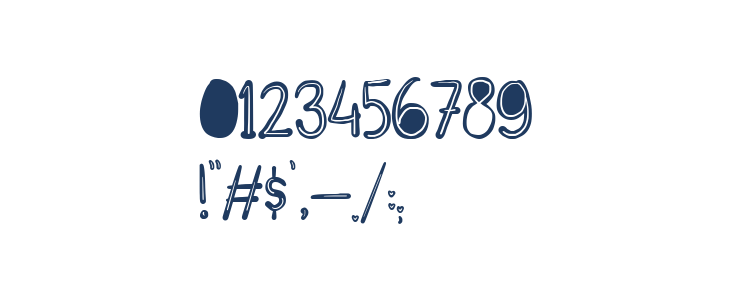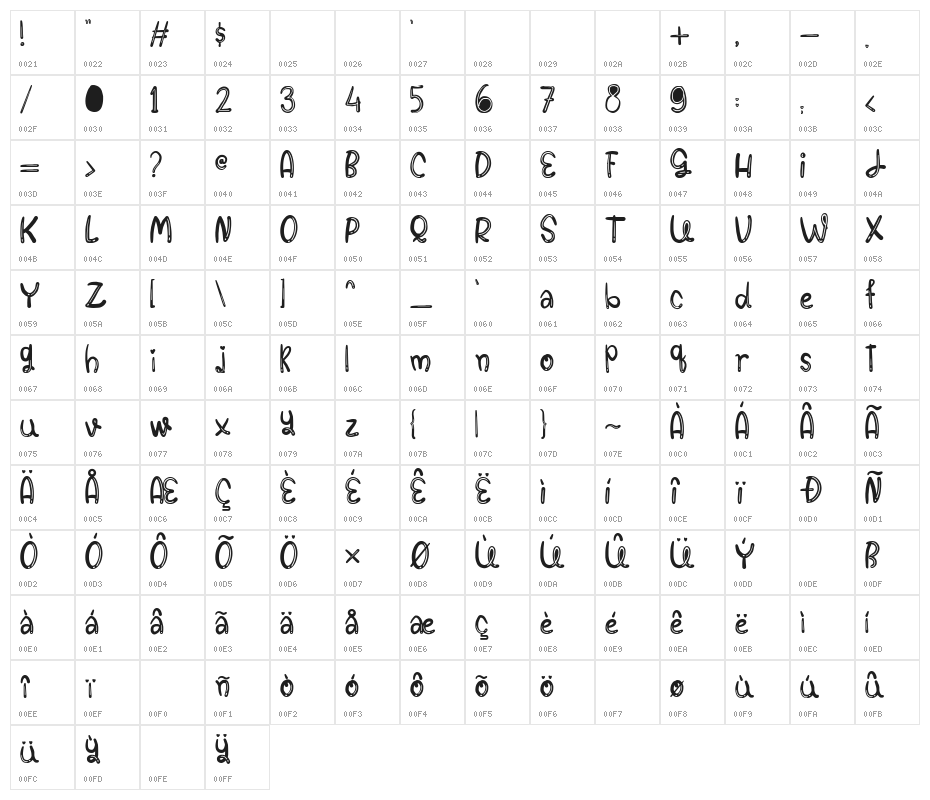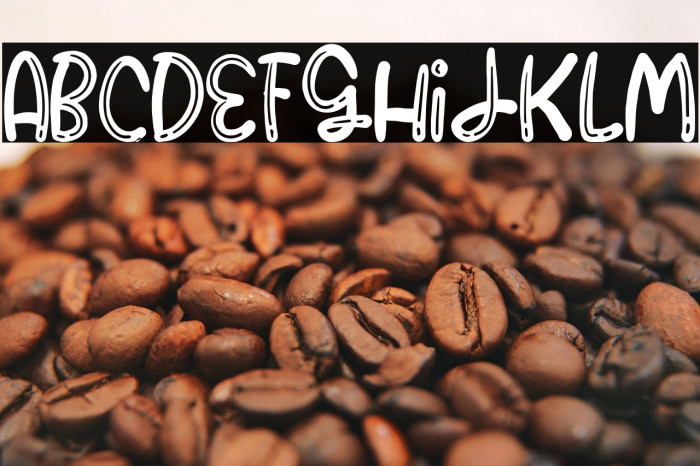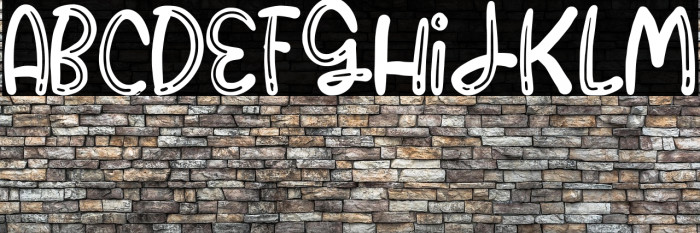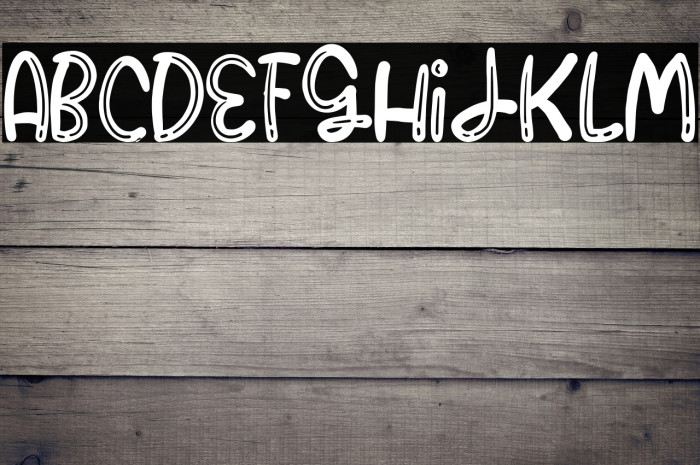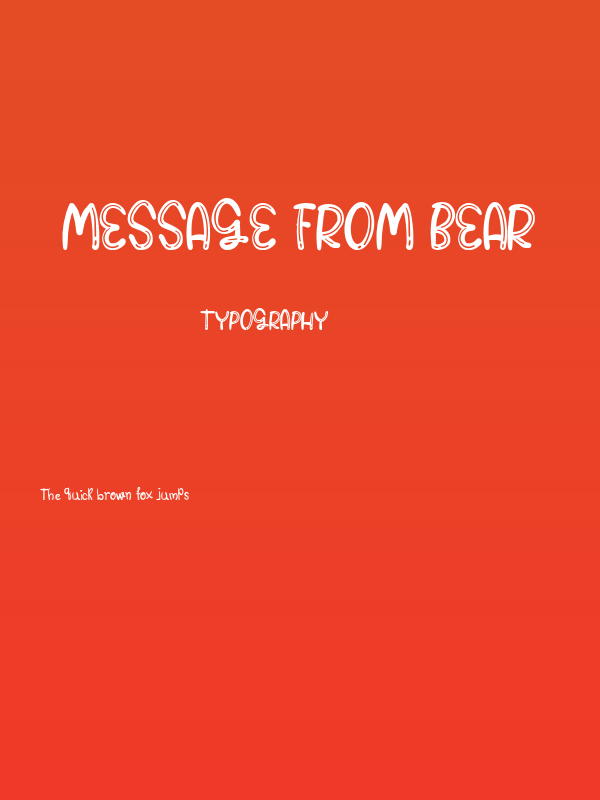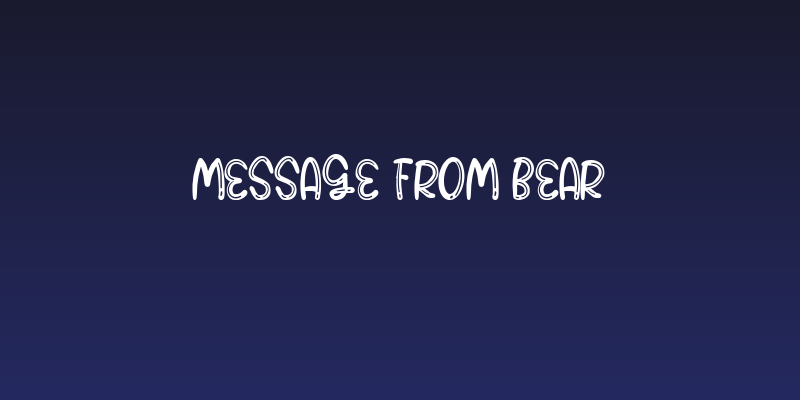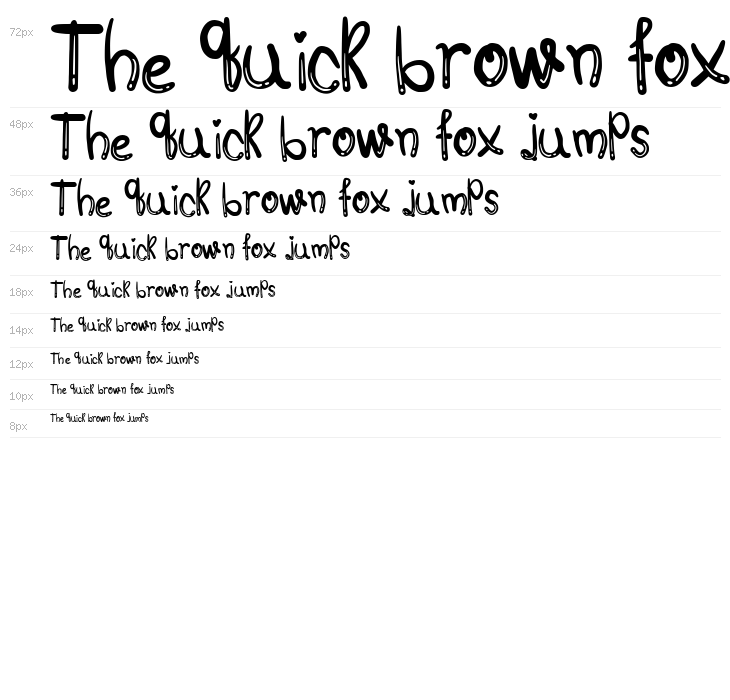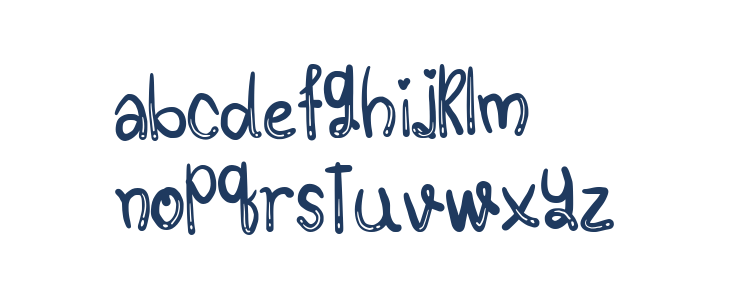
Message From bear Font
| समग्र शैली | Decorative |
| उपयोग का मामला | Logos, Headlines, Creative projects |
| सुझाए गए प्रोजेक्ट | Ideal for children's books, greeting cards, playful branding, and creative posters. |